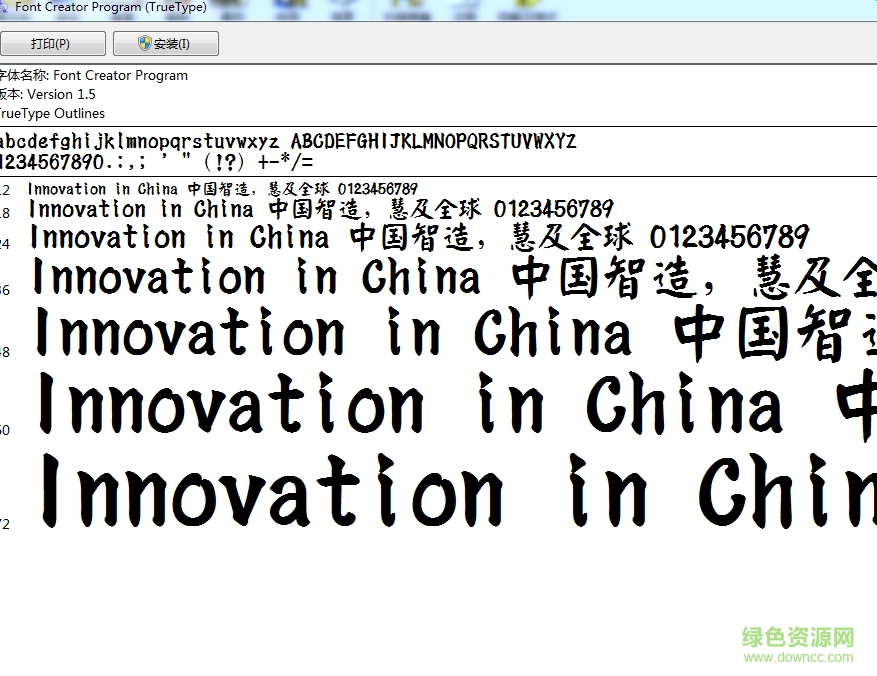
漢儀顏楷簡體是一款漢儀類顏值文雅風格字體軟件,顏楷體以楷書的優(yōu)美搭配濃濃的筆畫,整體效果非常好看醒目,適用于各大海報廣告標題的應(yīng)用,還有更多好看的字體歡迎來綠色資源網(wǎng)下載使用!
漢儀顏楷簡體是一款應(yīng)用于藝術(shù)設(shè)計方面的簡體中文字體,該字體筆畫粗壯,尾部的甩尾有力且有豐富的筆觸細節(jié),大字效果突出且引人注目;并且最大程度還原作者書寫字形,細節(jié)表現(xiàn)完整,且字庫完整,可以廣泛應(yīng)用于名片設(shè)計、新聞媒體、宣傳海報、ppt、影視制作以及內(nèi)容用字等領(lǐng)域。
此字體筆畫細膩行如流水,完美展現(xiàn)現(xiàn)代楷體的正式風格,現(xiàn)代氣息十足,整體效果比較工整好看,此字體老女老少皆宜使用!